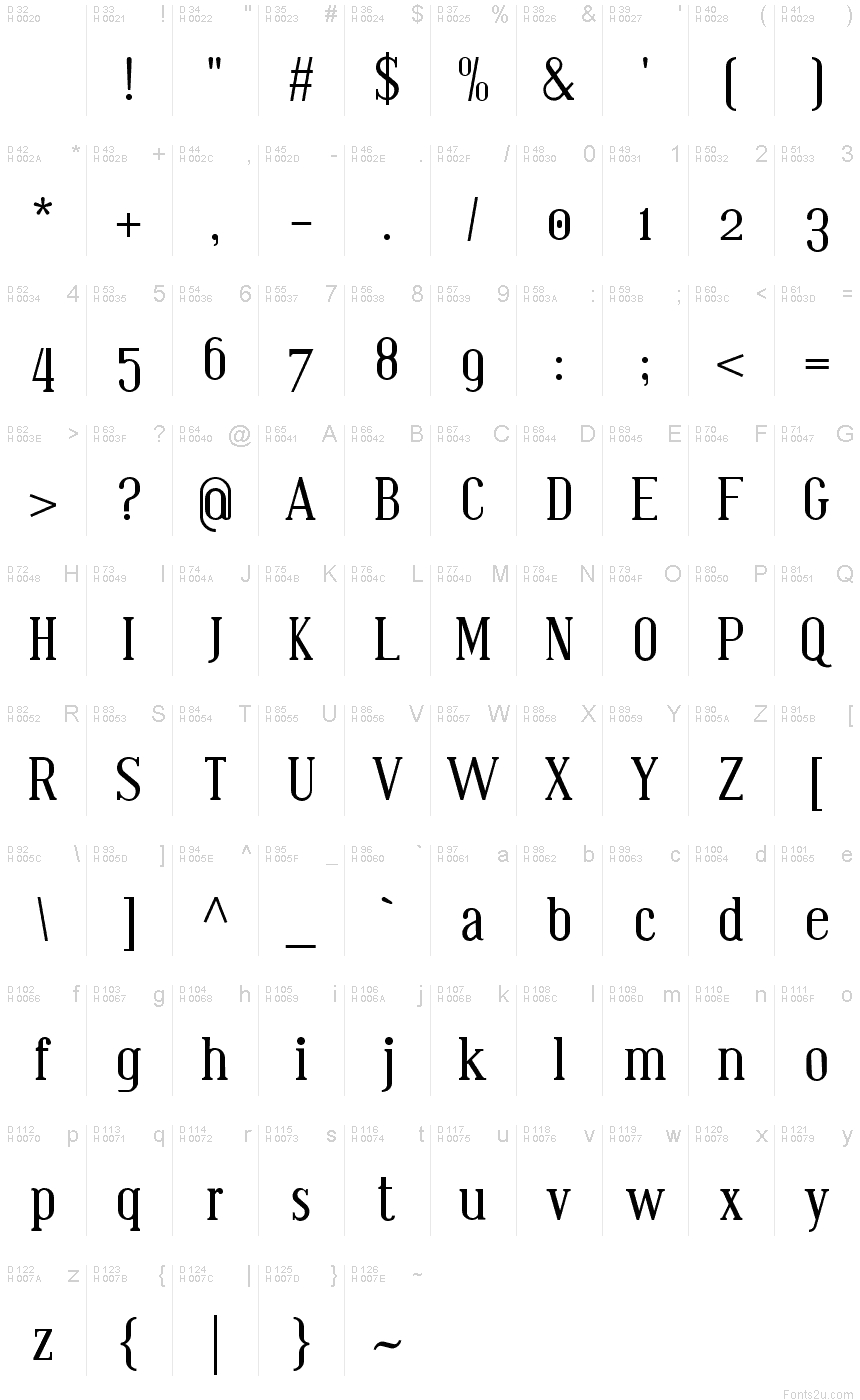
Bistecca من استوديو Studio Kmzero هو خط لاتيني (serif) عصري ومجاني يضفي لمسة من الأناقة الهادئة. تمزج الحروف بين التباين العالي والمنحنيات الناعمة والمستديرة، مما يمنح الخط طابعاً مصقولاً بعيداً عن الجمود؛ النقطة الكبيرة فوق حرف i والانسيابية الواسعة في الحروف الصغيرة تمنحه نبرة أدبية وتحريرية مميزة.
يناسب الخط بشكل طبيعي ترويسات المجلات، وتغليف المنتجات الفاخرة، وهويات المطاعم، وأغلفة الكتب، والعناوين القصيرة على الملصقات، حيث يمكن لخط مجاني بهذا التباين أن يحمل التصميم بفضل أناقته وحدها. استخدمه للعناوين الرئيسية، والشعارات النصية (wordmarks)، أو الاقتباسات القصيرة عندما تبحث عن مظهر متوازن، مفعم بلمسة حسية، وواضح كخط serif بعيداً عن التكلف الزخرفي.